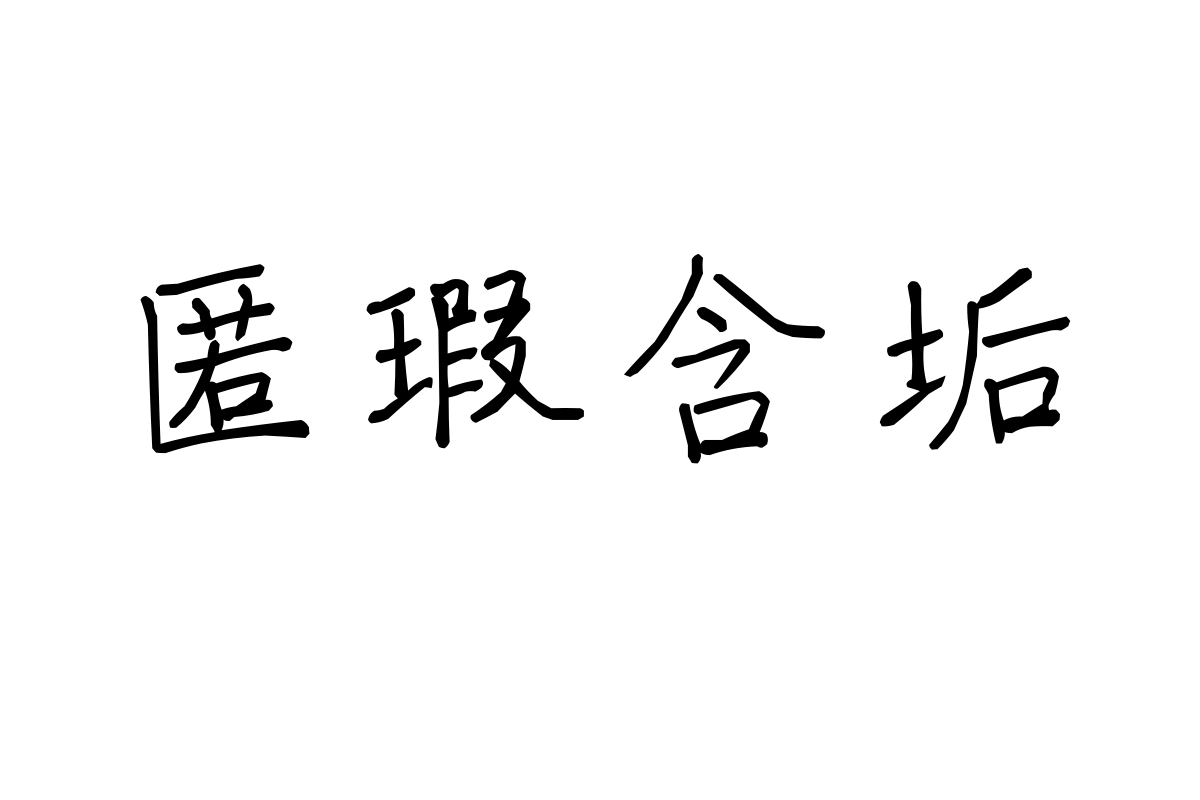
三极崇德行楷是一种书法字体,由书法家张永和在2006年设计。这种字体具有独特的风格和特点,被广泛应用于各种场合,包括商业、广告、印刷等。
三极崇德行楷的笔画流畅,结构紧凑,线条粗细适中,给人一种清晰、明了的感觉。它既有传统的韵味,又不失现代的气息,是书法艺术与现代设计的完美结合。
这种字体的特点是:笔画简洁有力,结构严谨,线条流畅,给人以美感和力量感。它的每一个字都充满了生命力,仿佛在讲述一个个故事,让人感受到作者的情感和思想。
总的来说,三极崇德行楷是一种非常优秀的书法字体,无论是用于商业还是其他用途,都能给人留下深刻的印象。